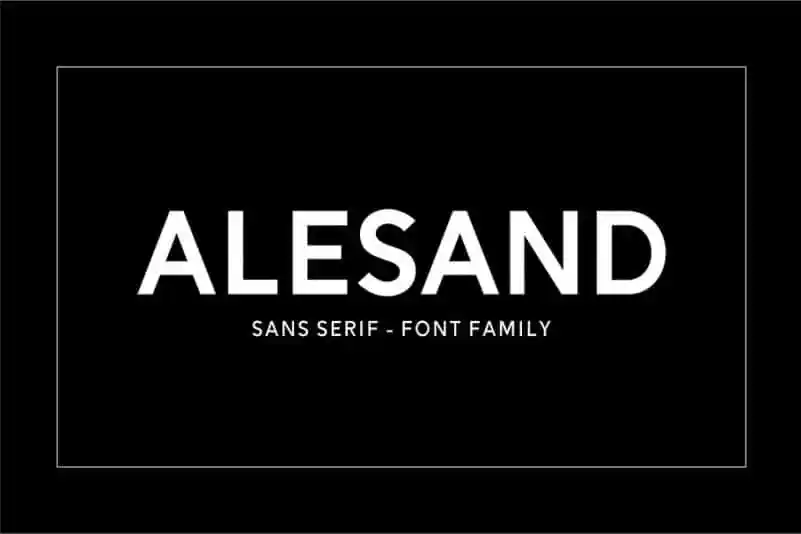
Introduzimos Alesand Sans Font Family, uma nova família de tipo geometrica e sans serif com baixa contraste e grandes contornos abertos que conferem ao tipo uma aparência um pouco mais assertiva e contemporânea. Este novo conjunto de fontes foi projetado com equilíbrio e versatilidade em mente. Alesand Sans oferece a vantagem adicional de estilos como linha-dura e extrusão, o que torna sua utilização extremamente simples e perfeita. Um recurso útil inclui duplicar o ‘Extra Bold’ layer e alterar para ‘Outline, Extrude’, permitindo automaticamente que o tipo se desloque para você. Essa característica simplifica a criação de combinações de tipos harmoniosas e elegantes.